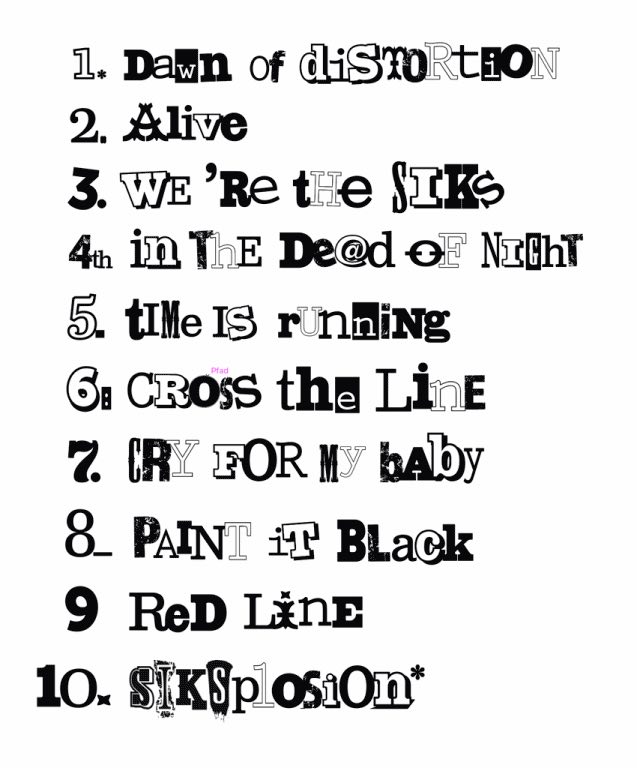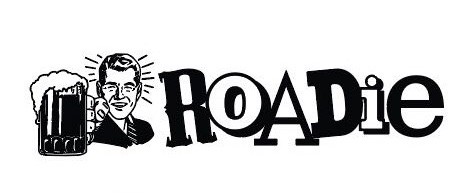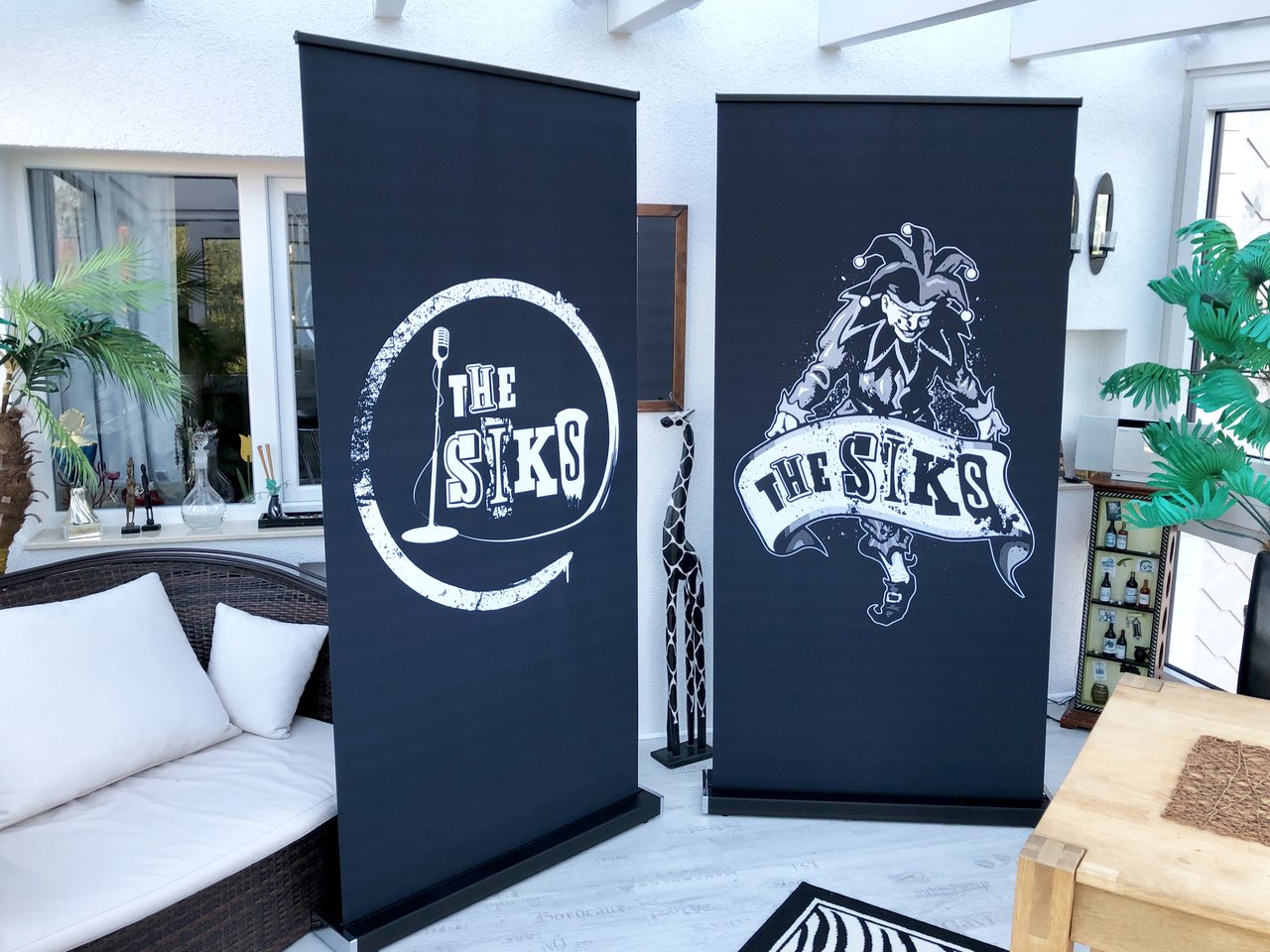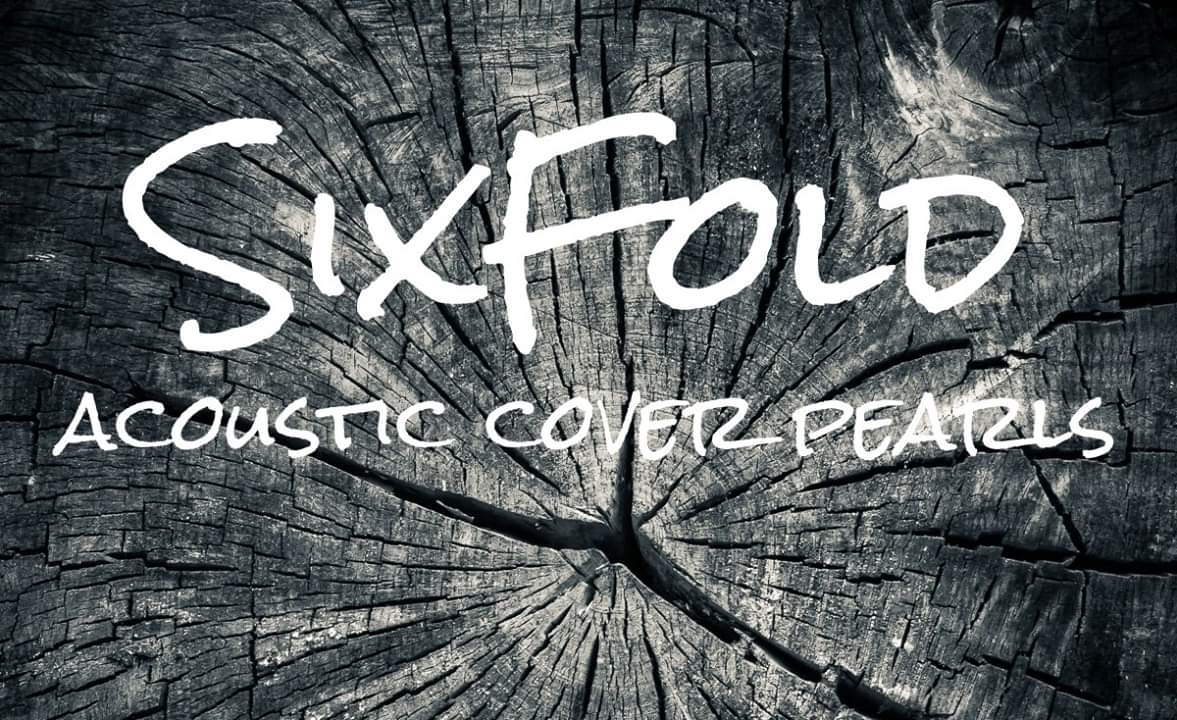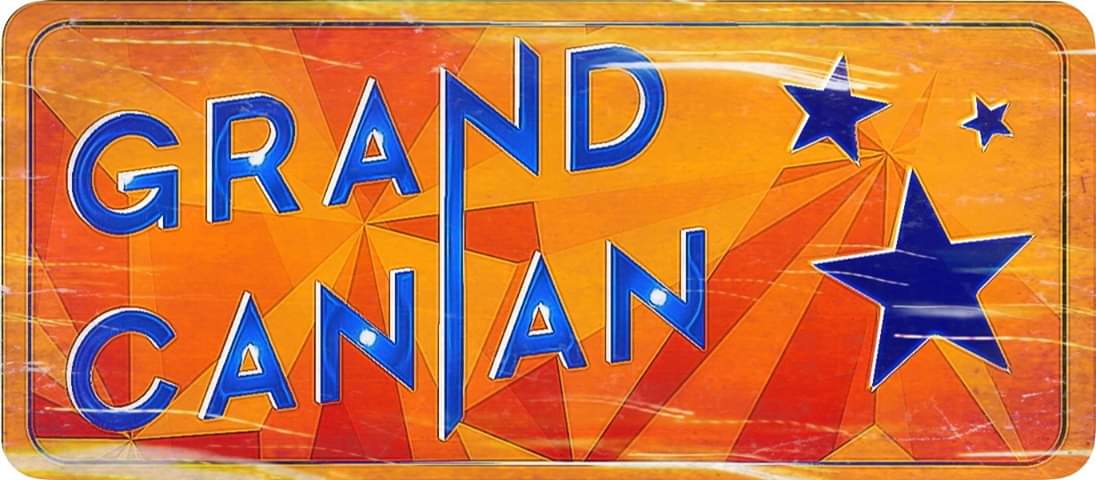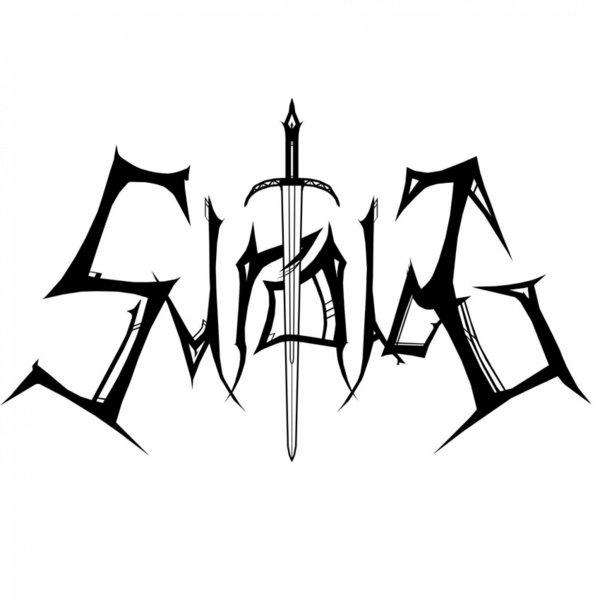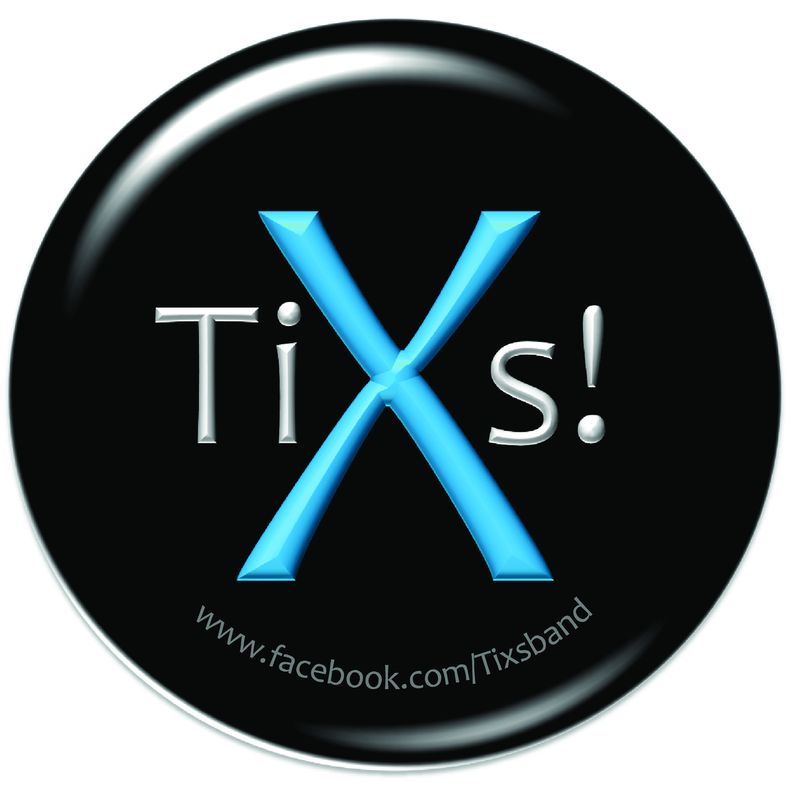
Euer Bandlogo-Artwork-Schriftart... her damit...!
am schlimmsten finde ich ja so Metalband geschnörksel, bei dem man nichts lesen erkennen etc kann
Nur wenn es unlesbar ist, ist es gut! bass-guitar:rock:
Ne, dass soll heißen "Schwert im Wald von Tschernobyl"
Das Logo für meine aktuelle Combo ist einfach gehalten – Zeitlos Futura, passend zum Bauhausjahr; die ZZ zu einem liegenden Auflösungszeichen zusammengeschoben.
Wir sind für ein Projekt zusammengekommen, um Stücke der Musiker aus dem Club 27 in eigenen, verjazzten Interpretationen zu spielen und singen.
Daher, und weil sich ein Teil der Combo bei meinem Junggesellenabschied in zweifelhaftem Zustand Helge Schneiders Jazzclub angeschaut hat. Der Name war dann erstmal Jazzclub 27, das fand die Sängerin dann aber anmaßend, so dass wir für die Zahl einfach die Quersumme genommen haben :D
Das ist mein Name.
Triskele und Schrift beides selbst entworfen und gezeichnet.
Bei Uns war die Namensfindung auch echt schwierig. Über Wochen nichts konsensfähiges. Letztlich waren alle schon fast genervt...Wir machen halt Acoustic Cover. Was da alles für Vorschläge kamen...Hammer. Einer meiner Favoriten ist immer noch "Christel Mett Orchestra", aber das will natürlich nicht recht zu unserer Musik passen.
Schriftart sollte auch irgendwie zum Bandkonzept passen und vor allen Dingen "free for commercial Use" sein.
Entstanden ist dabei bislang das:
....und das finde ich bislang, gemessen an unserer Musik stimmig und passend....
Astreines Logo.
Ist das Bild mit dem Narren (ohne den Schriftzug im Banner) eigentlich urheberrechtlich frei verfügbar? Oder habt ihr den selber gestaltet und gezeichnet, und seid somit auch Inhaber der Rechte? Auf jeden Fall sieht es sehr professionell aus. Die Lesbarkeit des Schriftzugs finde ich auch sehr angenehm. Und dabei ist es nicht mal irgend eine langweilige Standardschrift, sondern sieht echt "exklusiv" aus.
Das ist alles für uns designed. Es gibt ein ganzes Alphabet und jeden Buchstaben in drei oder vier Ausführungen, damit diese immer kombinierbar sind. Damit können wir solche Sachen kreieren lassen:
Hier die Rückseite unseres letzten Albums.
... sozusagen ein erweiterter Sex-Pistols-Font, an den hab ich zuerst gedacht ... :confused:
Ja, das war die Grundidee! Ich kann aber nicht einmal beschwören, ob der Designer die überhaupt kennt. Der kommt vom Hiphop.